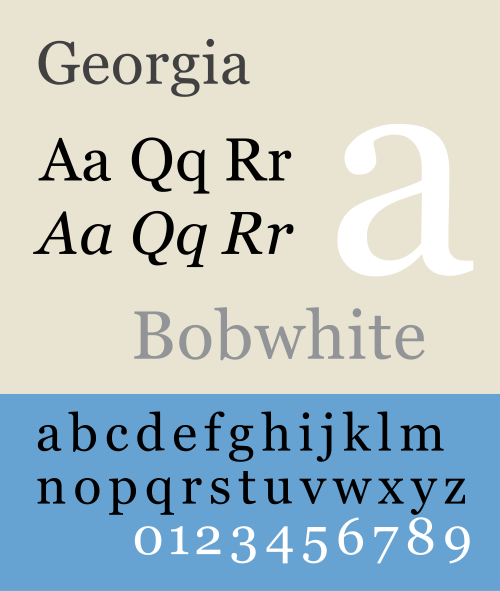
| カテゴリ | セリフ |
| デザイナー | マシュー・カーター |
| 作成日 | 1993 |
| リリース日 | 1996 |
ジョージアは、1993年にマシュー・カーターがデザインし、トーマス・リックナーがマイクロソフトのためにヒントを与えたセリフ書体である。小さく印刷したり、低解像度の画面で印刷してもエレガントで読みやすいセリフ書体を目指した。この書体は19世紀のスコッチ・ローマンのデザインにインスピレーションを受けており、マイクロソフトから連絡を受けたときにカーターが取り組んでいた印刷書体のデザインに基づいている。これは翌年ミラーという名前でリリースされることになる。 [1]この書体の名前は、タブロイド紙の見出し「ジョージア州でエイリアンの頭部が発見される」に由来している。[2]
デザイン
過渡期のセリフ体デザインであるジョージアは、太いストロークと細いストロークが交互になること、ボール型の終端、垂直軸など、19世紀初頭頃の「合理的な」セリフ体の伝統的な特徴を数多く備えている。2013年にジョージアとミラーの開発について語ったカーターは、「私はスコッチ・ローマンに精通していたが、かつては人気があったという事実に戸惑っていた...そして、完全に姿を消した」と述べている。 [3]数字のデザインは小文字、つまりテキスト数字であり、連続したテキストに溶け込むようにデザインされている。これは当時のコンピュータフォントでは珍しい特徴だった。[4]
Georgiaは、小さなサイズでもコンピュータのモニター上で明瞭に表示されるよう設計されました。[5] xハイトが大きく(小文字が縦に長い)、細い線はディスプレイ用や印刷でより鮮明に見えるように設計された書体で一般的なものよりも太くなっています。[6] [7]コントラストが低くセリフが太いため、 19世紀のClarendonのデザインに似ています。グリフは手動でヒント付けされました。[8]
Georgia の太字も異様に太く、ほぼ黒である。Carter は「Verdanaと Georgia は、バイナリビットマップが中心で、すべてのピクセルがオンかオフか、白か黒かだった。Verdana と Georgia の太字バージョンは、ほとんどの太字よりも太い。これは、1990 年代半ばにこれを行っていた当時、画面上では、ステムを 1 ピクセルより太くしたい場合、2 ピクセルまでしか太くできなかったためである。これは、印刷シリーズで従来よりも太さが大きくなっている」と述べている。[3]これらの異例のデザイン決定を考慮して、文書デザインの専門家であるMatthew Butterick は、画面表示に Georgia を使用している組織は、紙上で補完的でよりバランスの取れた読書体験を実現するために、 Miller のライセンスを取得することを推奨した。[9] [10]
Georgia書体は、過渡期のセリフ体デザインを再考したTimes New Romanに似ていますが、画面表示のデザインとして、xハイトが大きく、細かいディテールが少なくなっています。ニューヨークタイムズは2007年に標準フォントをTimes New RomanからGeorgiaに変更しました。[11]
ジョージアは「スコッチ・ローマン」と呼ばれる書体で、1810年から1820年にかけてアレクサンダー・ウィルソンとウィリアム・ミラーのスコットランドの活字鋳造所で販売された活字に由来する。トーマス・カーソン・ハンサードによると、これらはロンドンを拠点とするパンチカッターの リチャード・オースティンによってカットされた。ハンサードはオースティンの存命中に執筆しており、この帰属はオースティンの伝記作家アラステア・ジョンストンによって受け入れられているが、歴史家ジェームズ・モズレーはこの帰属に慎重な姿勢を示している。[12] [13] [14]
リリース
マイクロソフトは、1996年11月1日にこのフォントの初期バージョンをWebコレクションのコアフォントの一部として公開し、後にInternet Explorer 4.0の補助フォントパックにバンドルした。これらのリリースにより、WindowsとMacintoshの両方のコンピュータにインストールできるようになった。これにより、ウェブデザイナーの間で人気が高まり、ユーザーがコアフォントパッケージ(またはそれ以降のInternet Explorer)をインストールすれば、フォントの選択肢としてGeorgiaを指定したページは両方のタイプで同じように表示され、開発とテストが簡素化された。その作成者は、同じ目的で、Microsoft初のサンセリフスクリーンフォントであるVerdanaも同時に作成した。Georgiaの初期の公開リリースには、後にMillerでリリースされたものに似た、大文字と小文字の間の数字デザインが含まれていた。 [15] [16]マイクロソフトのタイプディレクターであるロバート・ノートンから、カーターはこれらをテキストに変更するように依頼されたが、カーターは後にこの決定を改良とみなした。[17]
ジョージアプロ
Georgiaの新バージョンは、姉妹フォントであるサンセリフフォントVerdanaとともに2011年にリリースされました。[18]
Georgia Pro という名のオリジナル フォントの拡張版には、次のような追加の書体とデザインが含まれています。
- 追加のウェイト(要約バージョンを含む)。
- 特殊な小文字大文字のデザイン。
- 文字セットの拡張。
- カーニングの拡張。
- 合字やライニング数字をデフォルトとして使用するなどのOpenType のタイポグラフィ機能。 [a]
拡張フォントは、Georgia と Verdana が入手しやすいためこれらを多用していたが、特定の用途のために追加バージョンを必要としていた組織向けに設計されました。
その他のバリエーション
マイクロソフトは、いくつかのバリエーションを委託している。ジョージアのバリエーションで、単一のウェイトで文字を追加したジョージア Ref は、Microsoft Bookshelf 2000、Encarta Encyclopedia Deluxe 99、Encarta Virtual Globe 99 にバンドルされている。ジョージア Ref の派生で太字とイタリック体を持つ MS Reference Serif も、Microsoft Encartaに含まれていた。しかし、マイクロソフトのフォント マネージャーである Bill Hill は、「個人的には、本の書体として完全に満足したことはありません。非常に暗く、"垂直" な感じがします」と書いている。また、マイクロソフトは、Microsoft Reader電子書籍製品用に、既存の書体 Berling とFrutigerのバージョンという代替案を委託したとも述べている。[22]それにもかかわらず、ジョージアは、いくつかの電子書籍アプリケーションにバンドルされている読書用フォントの中に含まれます。[23]
受賞歴
キリル文字フォントは1999年にキリルリツァで賞を受賞した。[24]
- ^ Georgia の標準版には合字デザインとライニング図が含まれています (少なくとも新しいバージョンでは) が、手動で有効にする必要があります。